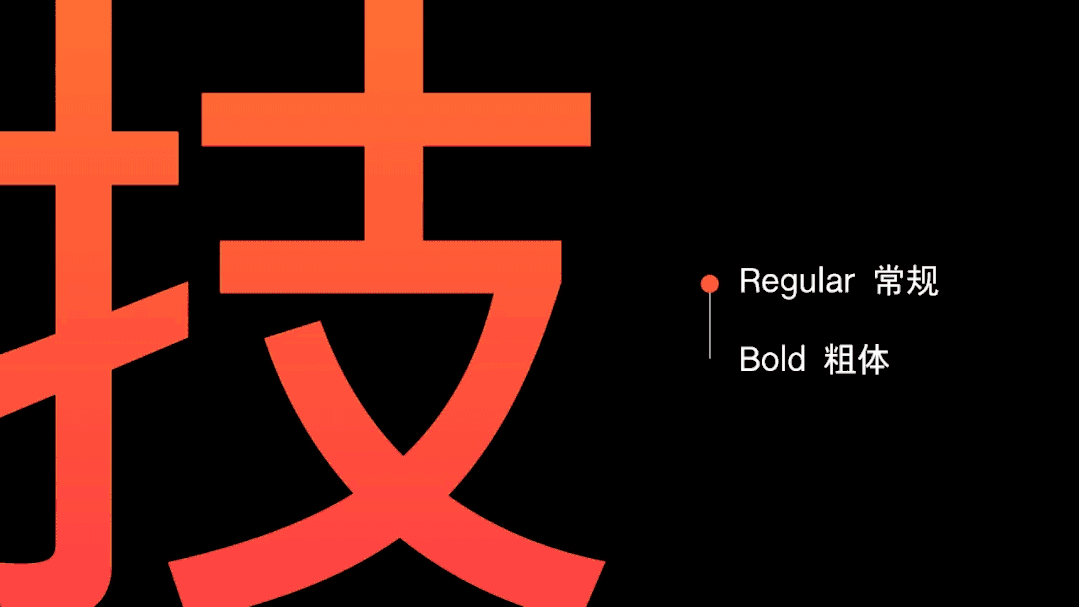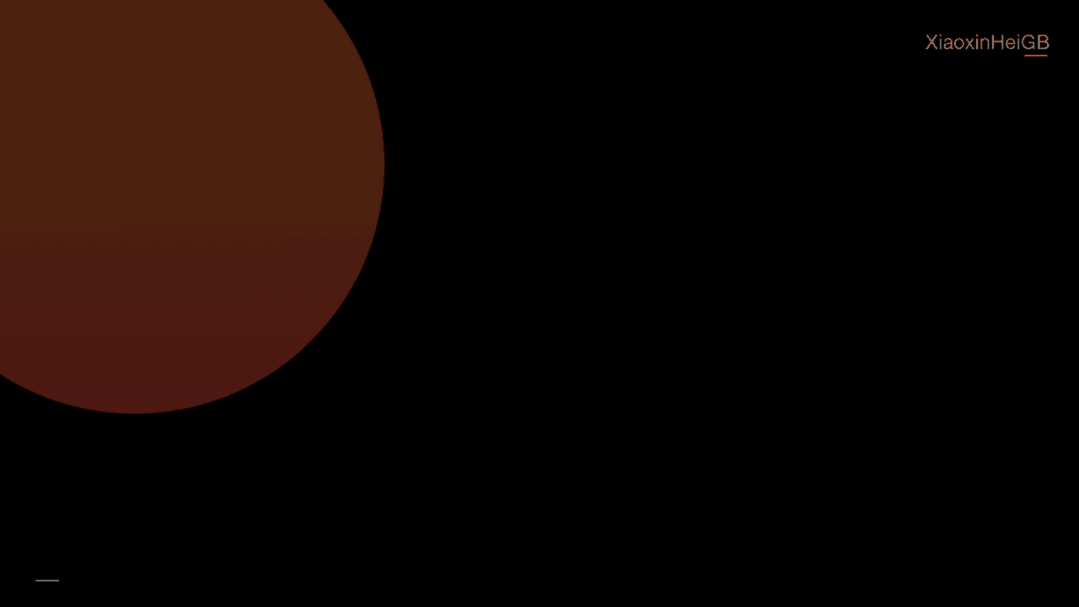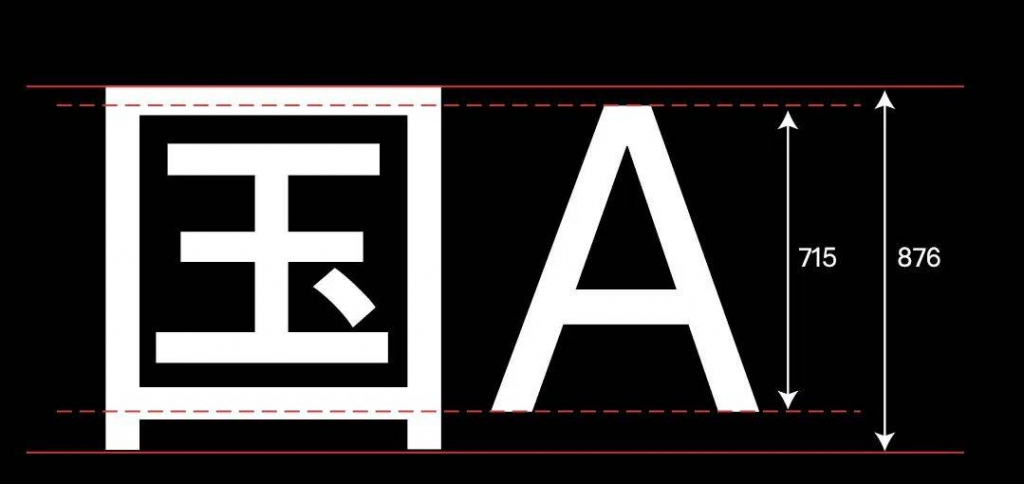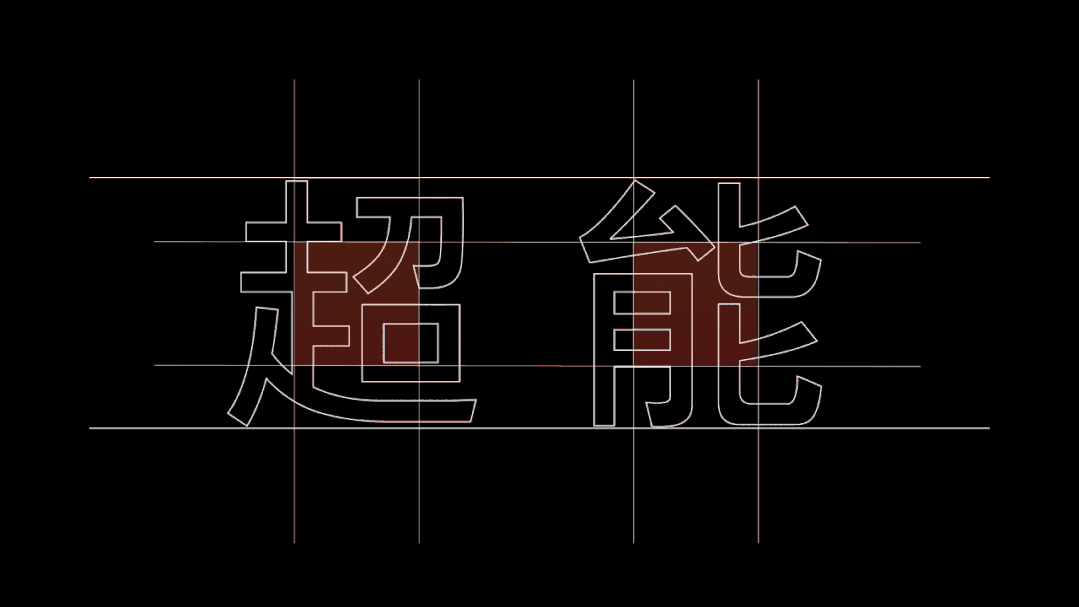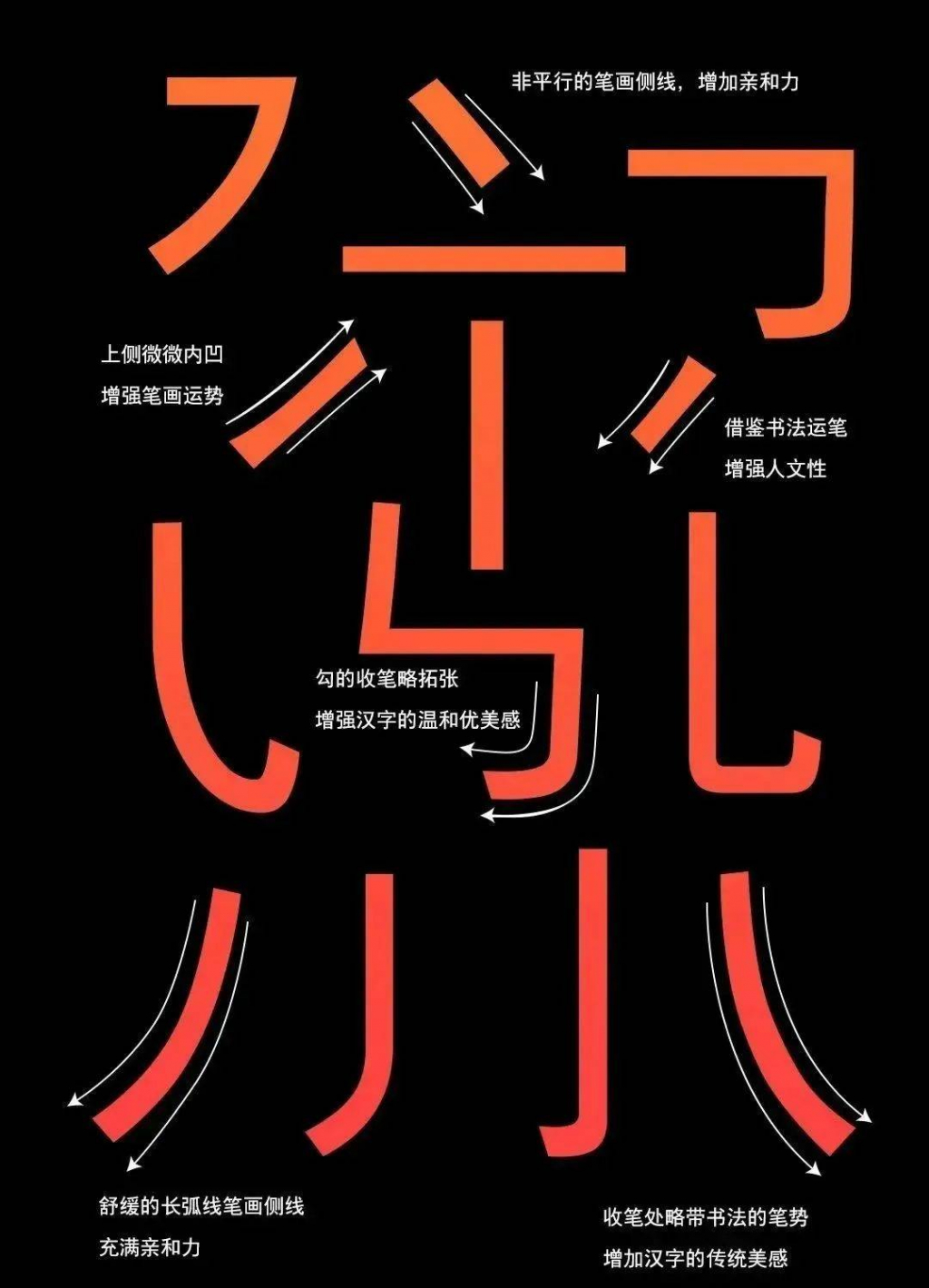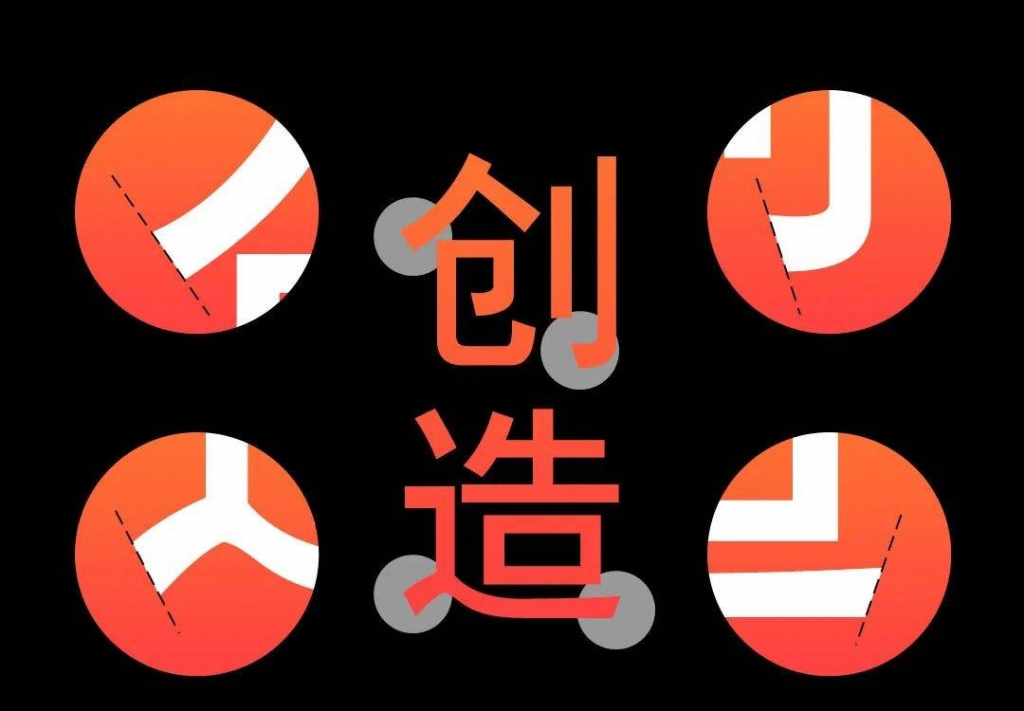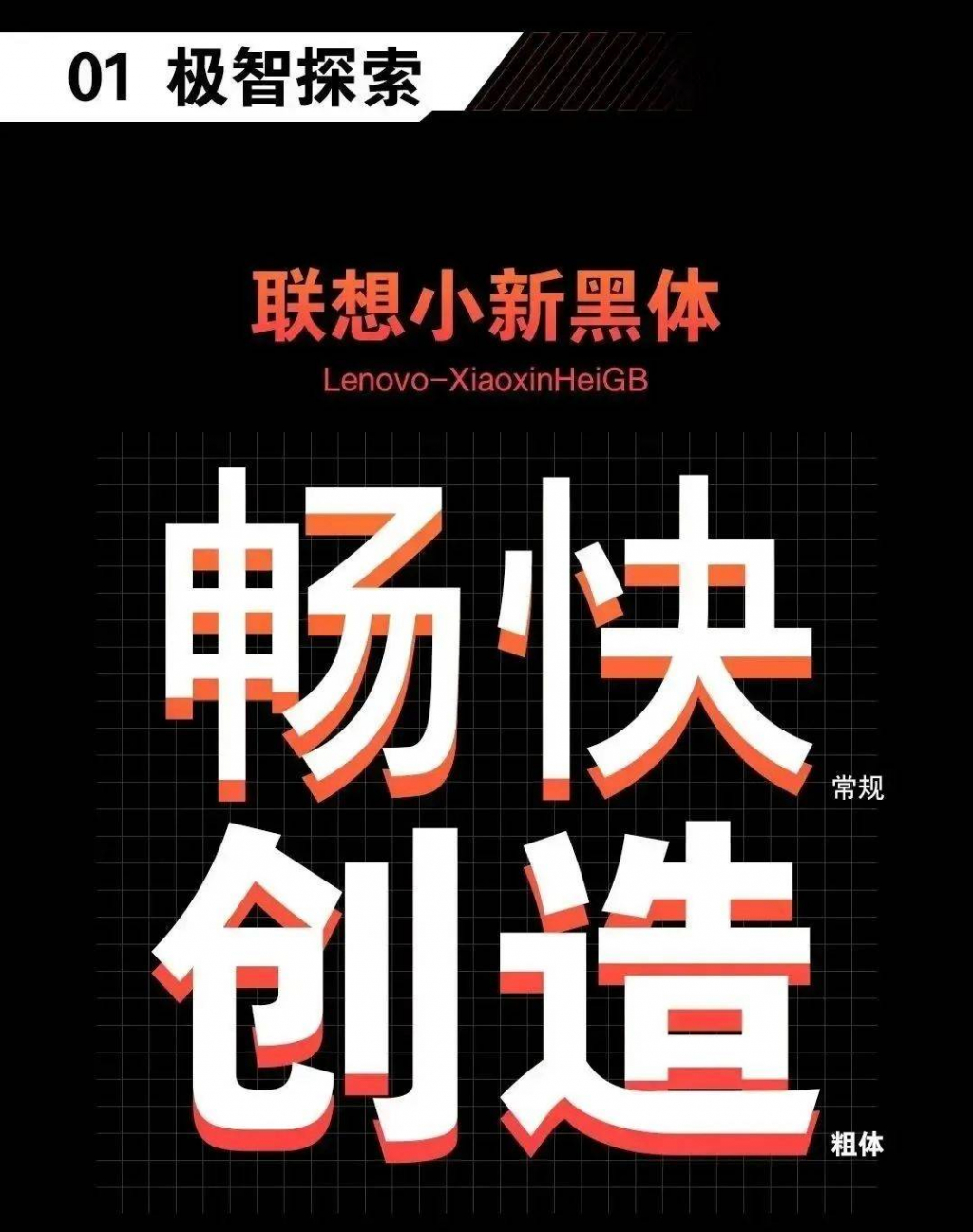
联想小新黑体
联想小新黑体是联想小新产品线联合锐字潮牌字库推出的一款免费商用字体。
联想小新黑体是基于联想小新“轻薄化”“高能化”的特点,以此为创作理念,以简约的笔画、精简的线条、柔和的弧度,打造出一款人文与科技交织的黑体字。
1、科技人文
联想小新黑体
平直极简的横竖笔画,突显品牌的科技感、未来感。常规体中笔画粗细的微弱差距,营造良好的视觉稳定性。
联想小新黑体
“人”字头等偏旁部首采用更具手写感的笔触,在中性的科技感中融合人文气息,创造出科技与人文的平衡,成就更好的视觉体验。
联想小新黑体
“口”字部首采用偏传统的出头造型,更符合用户的阅读习惯,优化辨识度与体验感。
2、视觉升级
联想小新黑体
为深度匹配品牌需求,联想小新黑体提供常规、粗体2款字重,同时在6763汉字基础上,增加400个常用汉字,可满足正文、说明文、标题等多种场景的应用需求。
联想小新黑体
联想小新黑体常规体
字面框与字身框占比82%左右,大段排版时增加阅读舒适性。相对缩小的字宫,带来更多的视觉关注力。
联想小新黑体粗体
字面框与字身框占比85%左右,重点信息、标题使用时醒目易读;相对稍微内收的字宫,提升了人文感。
联想小新黑体常规体|字母数字与汉字的基本高度比例在82%左右,在进行汉字与字母数字混排时,阅读舒适性更高。
联想小新黑体粗体|字母数字与汉字的基本高度比例在80%左右,。
3、笔画表达
笔画尾端设计兼顾传统字体的法度和意态,撇捺笔画的弧线流畅,末端收笔平缓柔和。
撇捺等弧线笔画采用了上端略微上扬、下端略微平直的线条,赋予字体灵动感,笔画两端采用接近垂直外侧切线的角度处理,既没有锐角端面的犀利感,又没有纯垂直端面的冰冷感,整体营造出舒适柔和的人文美感。
4、中西兼备
联想小新黑体
西文的笔画末端统一采用平切的手法,笔画转折处呈现自然流畅的弧线,整体简洁又不失优雅,呈现清爽利落的秩序感与精简的视觉效果。
联想小新黑体字体效果预览